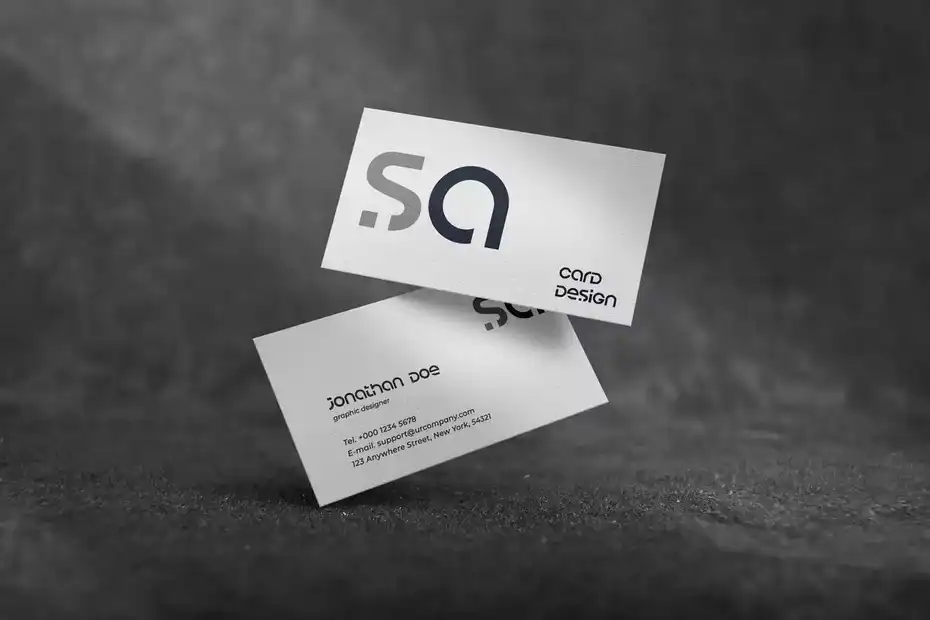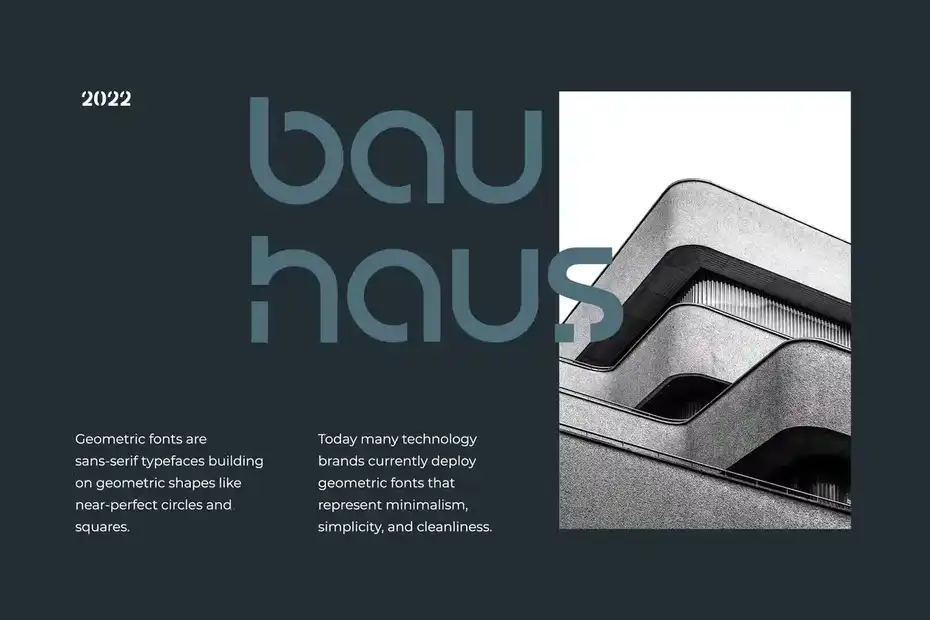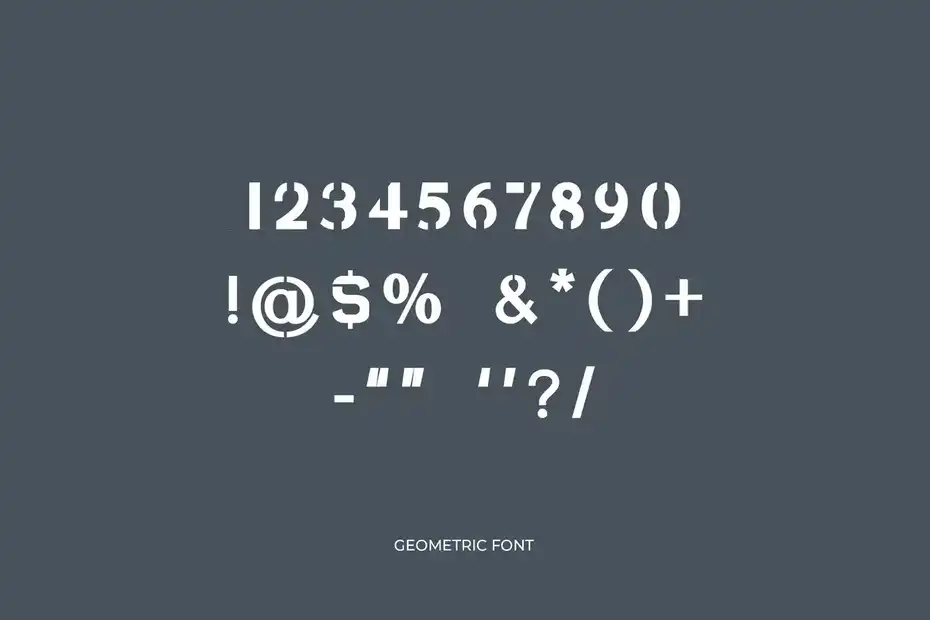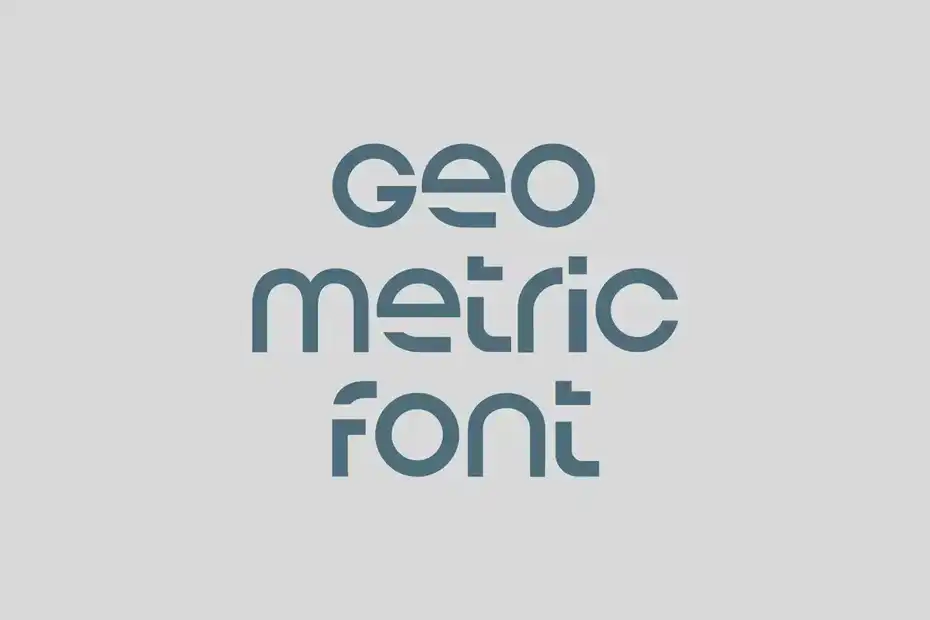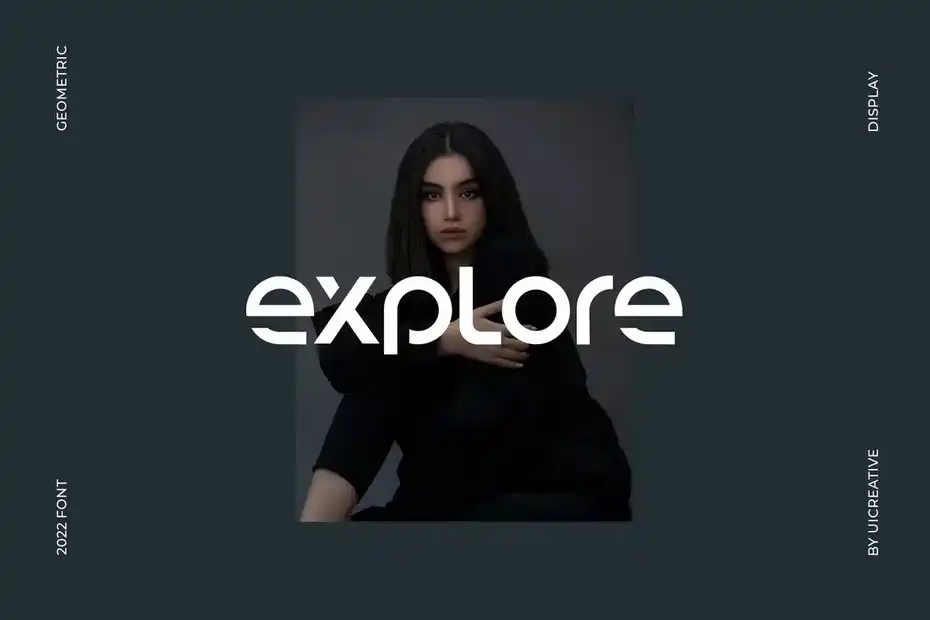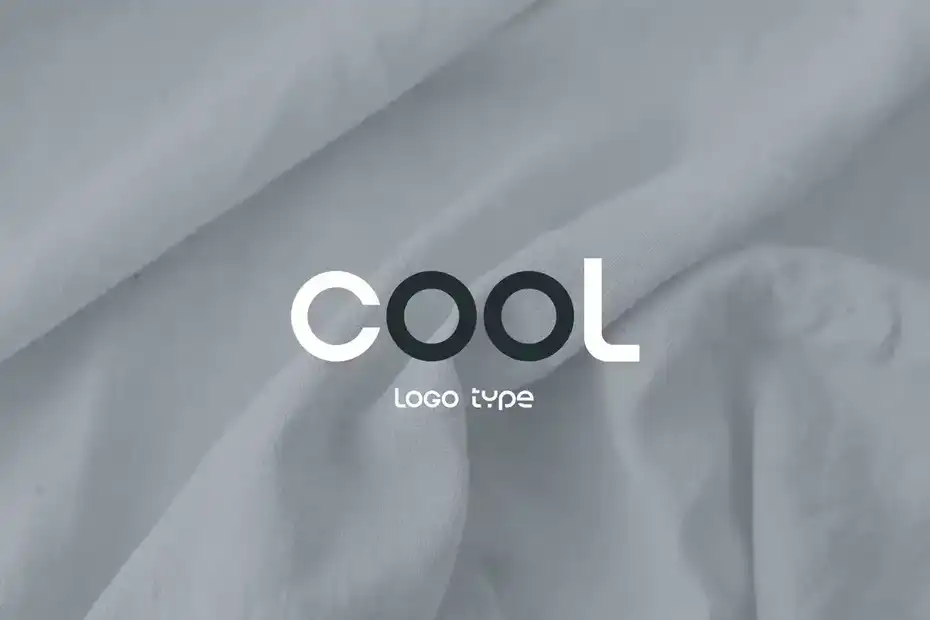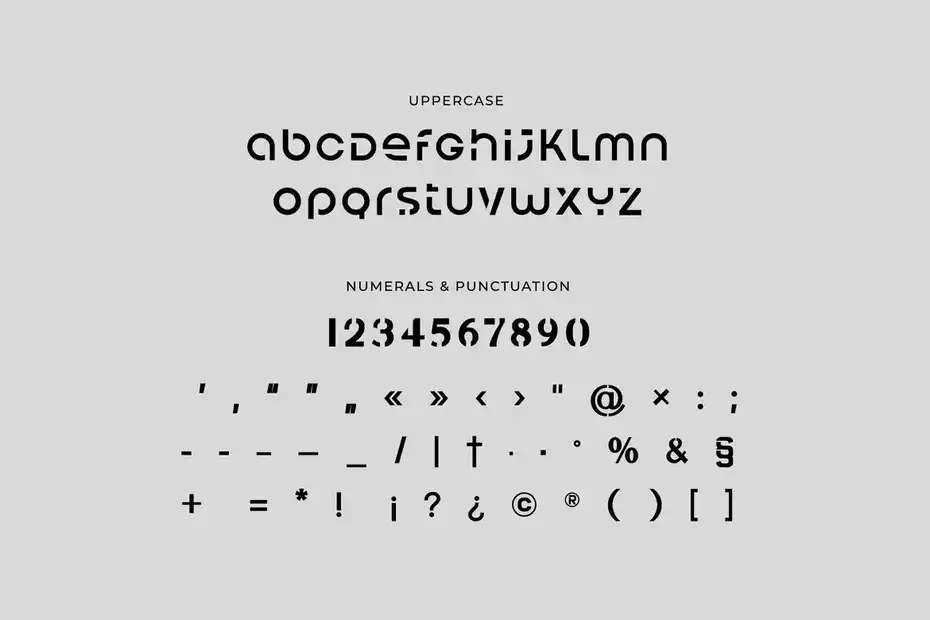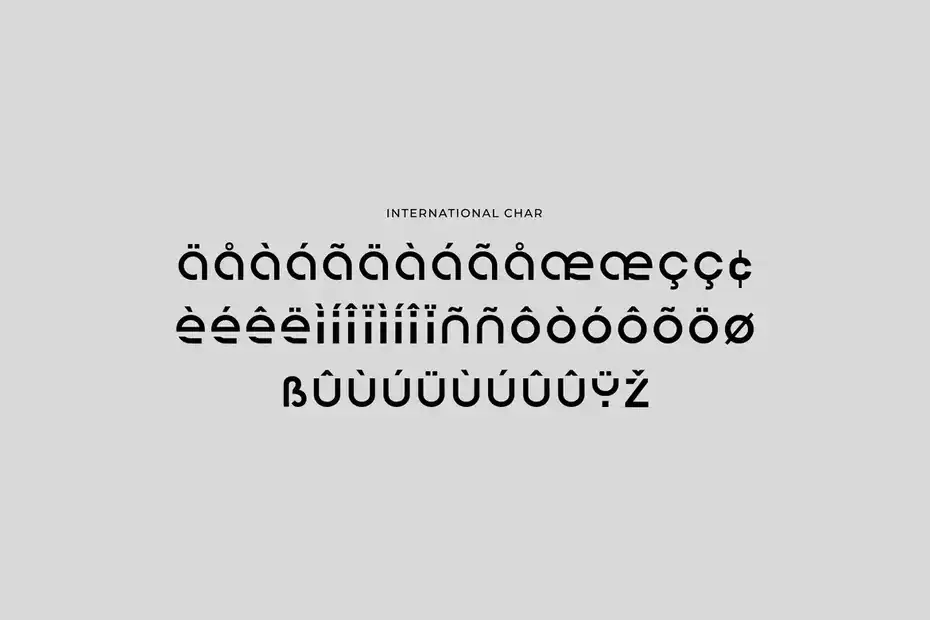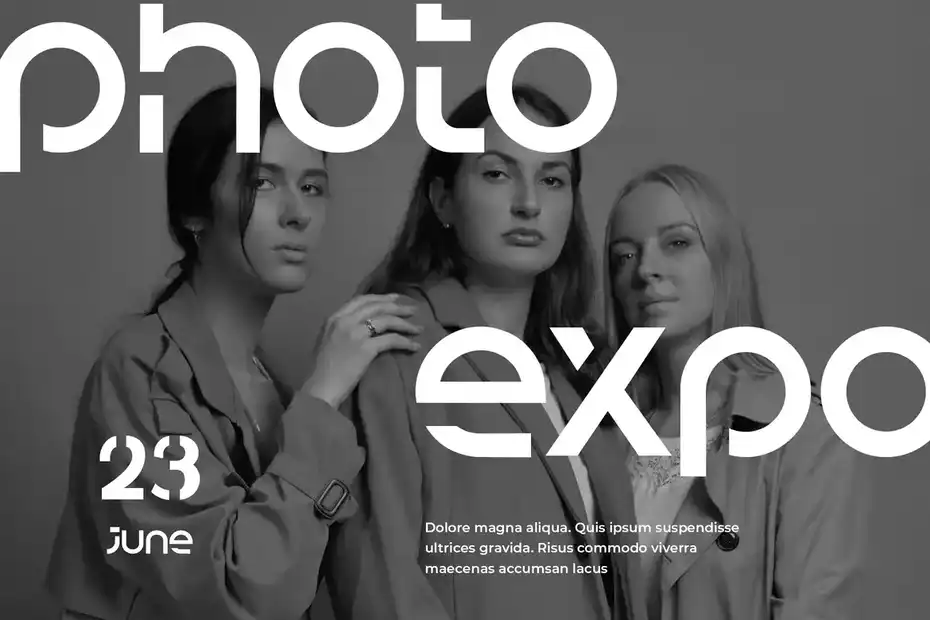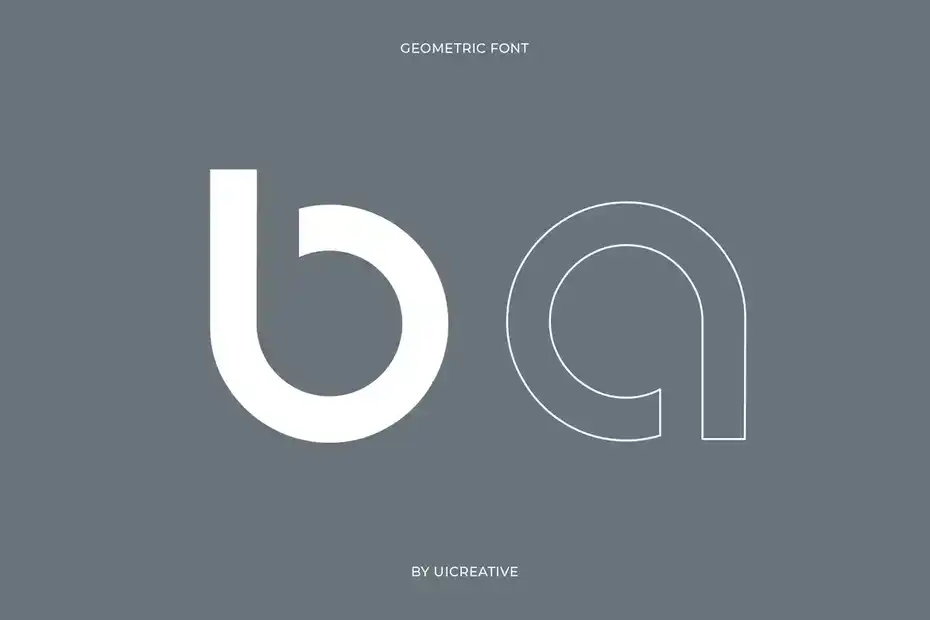
دانلود فونت انگلیسی Pure Mechanic Futuristic Sans Serif Font
فونت انگلیسی Pure Mechanic Futuristic Sans Serif Font : این مجموعه شامل یک فونت فانتزی است که برای امضا، برندینگ، لوگو، کارت، عروسی، نقل قول‌ های تایپوگرافی، کاور مجله یا کتاب، سربرگ وب‌سایت، لباس، طراحی بسته‌ بندی و غیره مناسب میباشد.